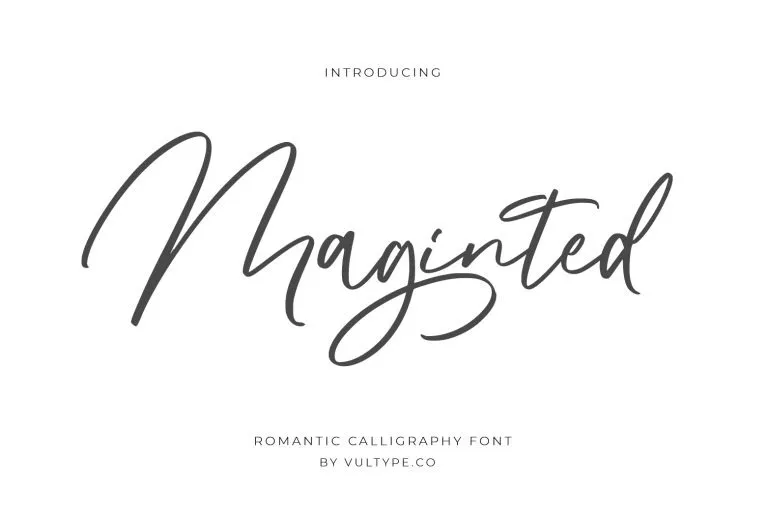
Maginted Font – Download Grátis
A ‘Maginted Font’ é uma elegante tipografia script, leve e agradável aos olhos que foi criada pela grandefonts. Com sua textura limpa, fina e suave, ela combina perfeitamente com qualquer projeto de design gráfico moderno ou sofisticado. Seja para criar um slogan memorável, decorar uma publicação de moda ou adicionar um toque atraente em um poster de festa, a ‘Maginted Font’ é o elemento perfeito que tornará seu trabalho único e chamativo. Como fonte script, ela oferece flexibilidade sem igual na criação de mensagens visuais sofisticadas ou criativas, garantindo que qualquer projeto se destaque. Não importa o formato do seu design, a ‘Maginted Font’ pode transformá-lo em algo ainda mais impressionante e memorável.